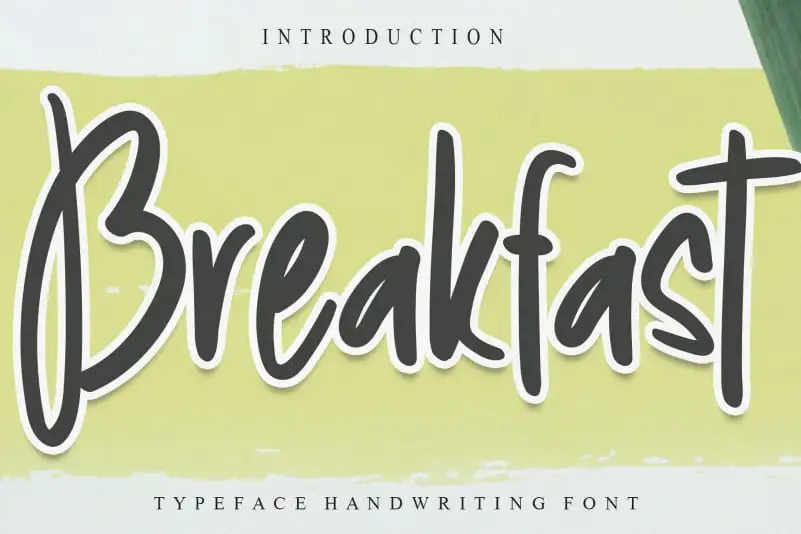
Breakfast Brush Font – Download Grátis
Aqui está uma descrição envolvente para a página de download da font ‘Breakfast Brush Font’, adaptada aos requisitos fornecidos: A font Breakfast Brush Font é perfeita para aqueles que buscam um toque único e criativo no design de seus projetos digitais. Esta elegante font escrita à mão oferece uma experiência visual agradável, com traços fluidos e nuances únicas que adicionam profundidade e personalidade aos textos. Com sua tipografia em estilo brush, Breakfast Brush Font é ideal para designers buscando dar um toque diferenciado a layouts de blog, elementos visuais para redes sociais, ou qualquer projeto onde deseja destacar o texto. O designer creativeletter criou uma fonte pensada para aqueles que valorizam tanto a simplicidade quanto a sofisticação na composição visual. Esta font escrita à mão é perfeita para quem quer incorporar um toque mais pessoal e expressivo em seu trabalho. Perfeito tanto para uso pessoal como profissional, Breakfast Brush Font é uma adição indispensável aos seus recursos de design digital.